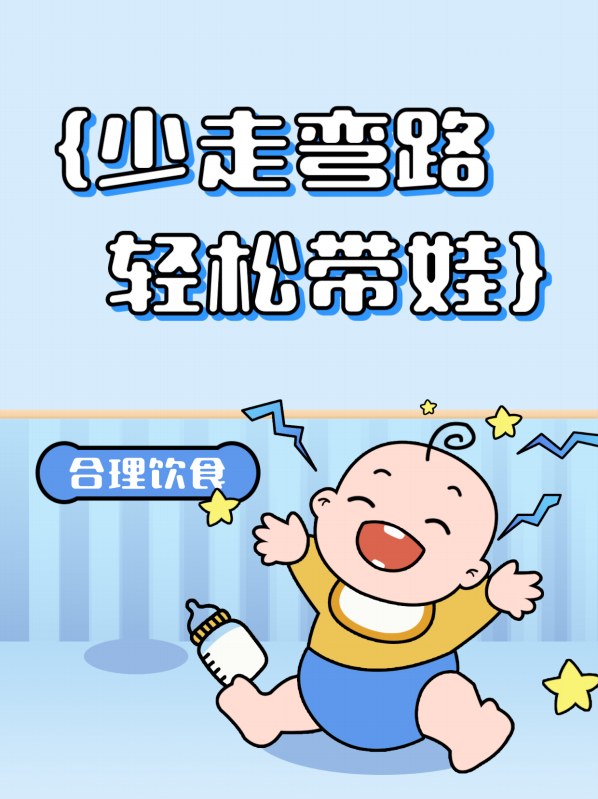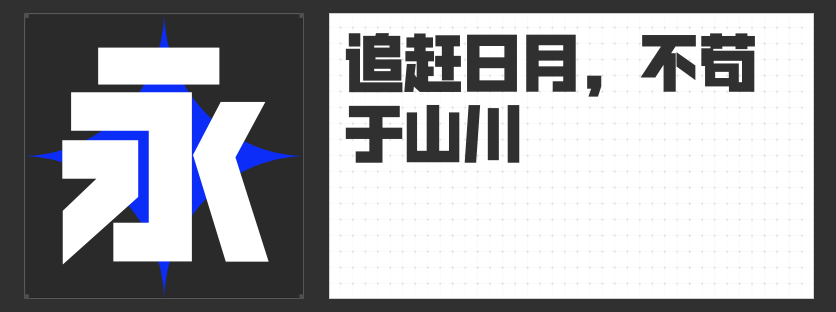
海报设计字体精选:解锁创意新境界
在海报设计的广阔天地里,字体宛如灵动的音符,奏响着视觉传达的华美乐章。今天,就为大家推荐四款独具魅力的字体,助力海报设计绽放别样光彩。
一、励字开拓者简 超黑
字型方正,中宫较大,重心恰到好处。它全部采用直线笔画,横平竖直间尽显棱角分明的硬朗气质。起笔和收笔以平切为主,内部几何处理使空间均匀分布,整体平衡感十足。尤为独特的是,部分钩笔画去钩处理,撇、捺、点竖直化,营造出强烈的镜像视觉效果。而且,它还包含众多网红流行用字,无论是潮流活动海报,还是科技感十足的宣传海报,都能凭借其独特的视觉冲击力,瞬间抓住观众的眼球。
二、造字侠醉春风简繁 苍劲
整体风格自由率真、活泼灵动。单字结构周正却不失松弛,点画圆润,笔画间粗细过渡自然流畅。灵动的笔画走势赋予了它独特的字形风貌,仿佛带着春风的轻盈与洒脱。在文化活动、艺术展览等海报设计中,它能为画面增添一份灵动与诗意,让海报更具艺术感染力。
三、励字逆反差圆舞简 超级黑
是字型方正、软硬兼备的逆反差圆弧字体。在逆反差直线版基础上,撇、捺、钩及部分点笔画运用弧线处理,弧度饱满。中宫较大,重心平稳,笔画对称。这种刚柔并济的特质,使它在时尚、娱乐类海报设计中表现出色,既能展现硬朗的气质,又不失柔和的美感,为海报增添一份独特的创意魅力。
四、高手庆科墩墩体 大黑
字型略扁工整,布白均匀,中宫宽阔,重心平稳。整体简洁可爱,是一款圆体。它采用直线结构设计,同时对笔画进行整体圆角处理,横细竖粗,横竖笔画端点和折笔处均运用圆角元素,笔画圆润饱满。在儿童产品、美食类海报设计中,它可爱的风格能迅速拉近与观众的距离,营造出温馨、愉悦的氛围。
这四款字体各具特色,在海报设计中合理运用,定能为你的作品带来意想不到的效果,开启创意设计的新篇章。